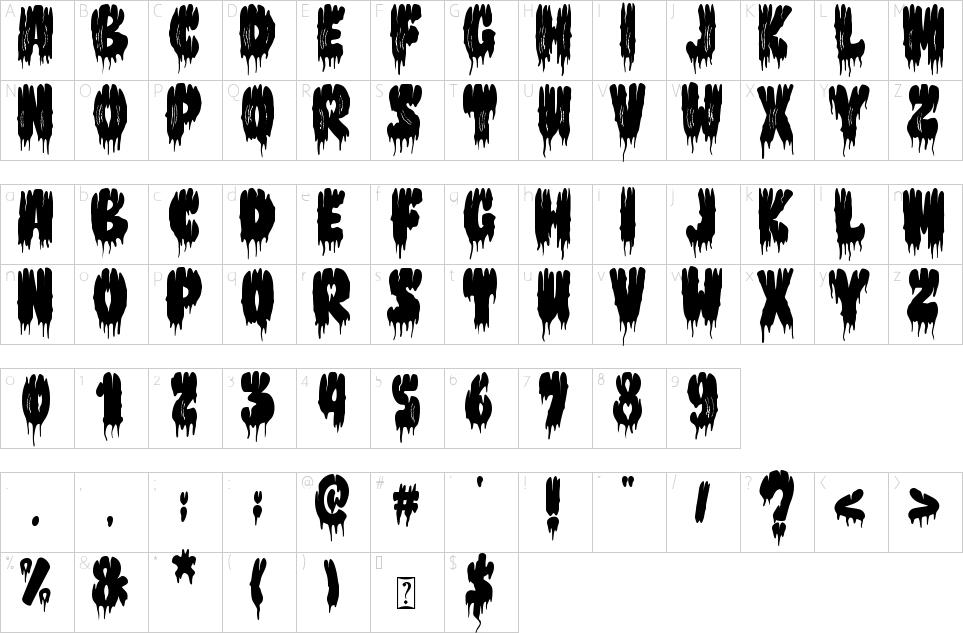
Monster Scratch Font – Download Grátis
A Monster Scratch é uma fonte inovadora que adiciona uma dose extra de energia e personalidade a qualquer projeto digital ou impresso. Desenvolvida pelo criativo Thomas Aradea, esta fonte foi projetada para dar um toque único e divertido aos textos. Com linhas arredondadas, curvas imaginativas e traços vibrantes, ela é perfeita para tornar seus documentos mais chamativos, seja em PowerPoint ou no site da sua empresa. Se você está procurando por algo que combine a simplicidade das fontes minimalistas com um toque de diversão e criatividade, a Monster Scratch pode ser exatamente o que precisava. Esta fonte é uma ótima opção para designers gráficos, redatores ou até mesmo pessoas que gostam de dar um toque especial aos seus emails ou posts no Facebook. Estamos felizes em anunciar que você pode agora baixar a Monster Scratch gratuitamente tanto no Windows quanto no Mac. Com apenas 1,348 downloads, é evidente o entusiasmo dos usuários por este único e peculiar estilo de fonte. Em suma, a Monster Scratch não só adicionará um novo nível de originalidade ao seu trabalho, mas também será uma peça importante em sua coleção de fontes gratuitas e incrivelmente únicas.